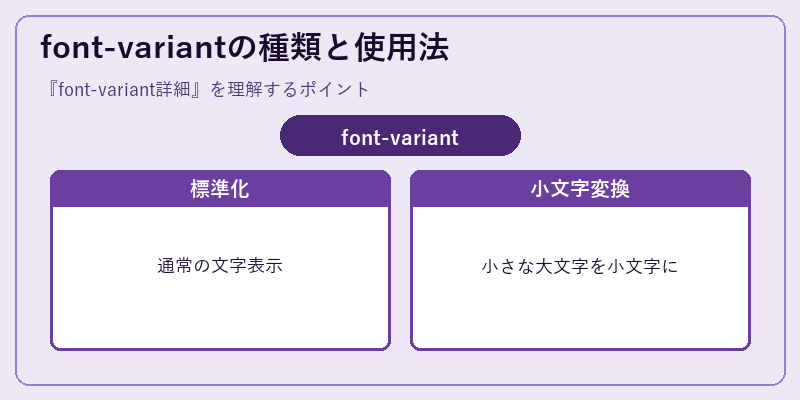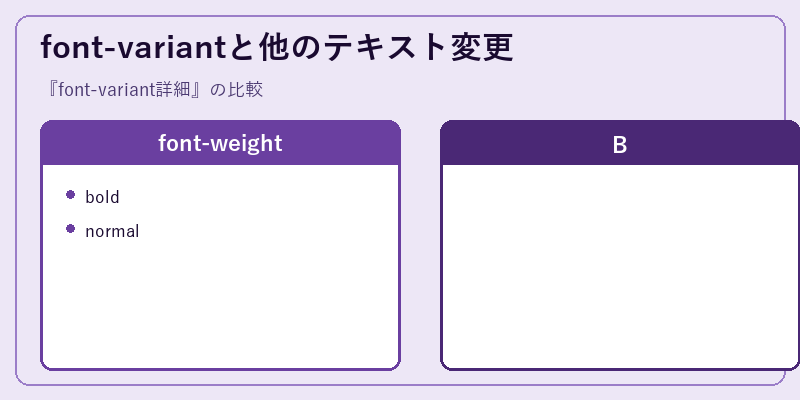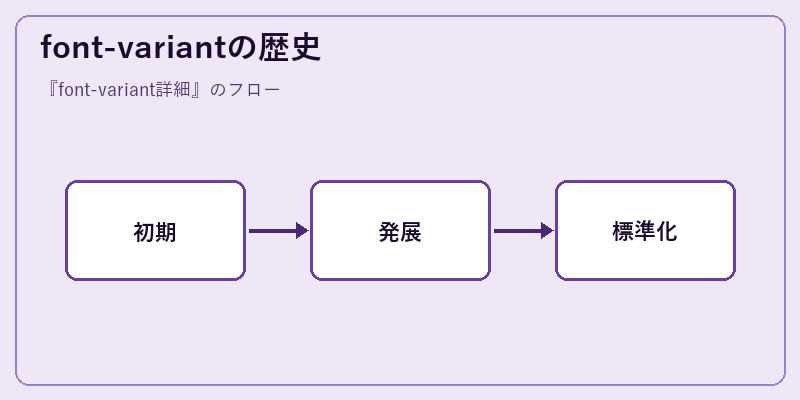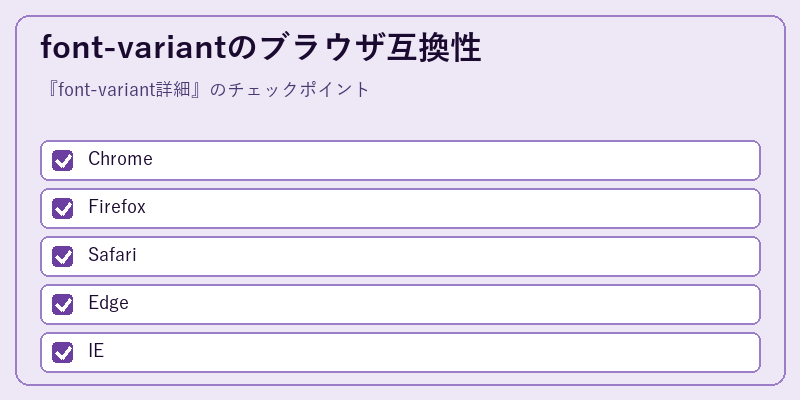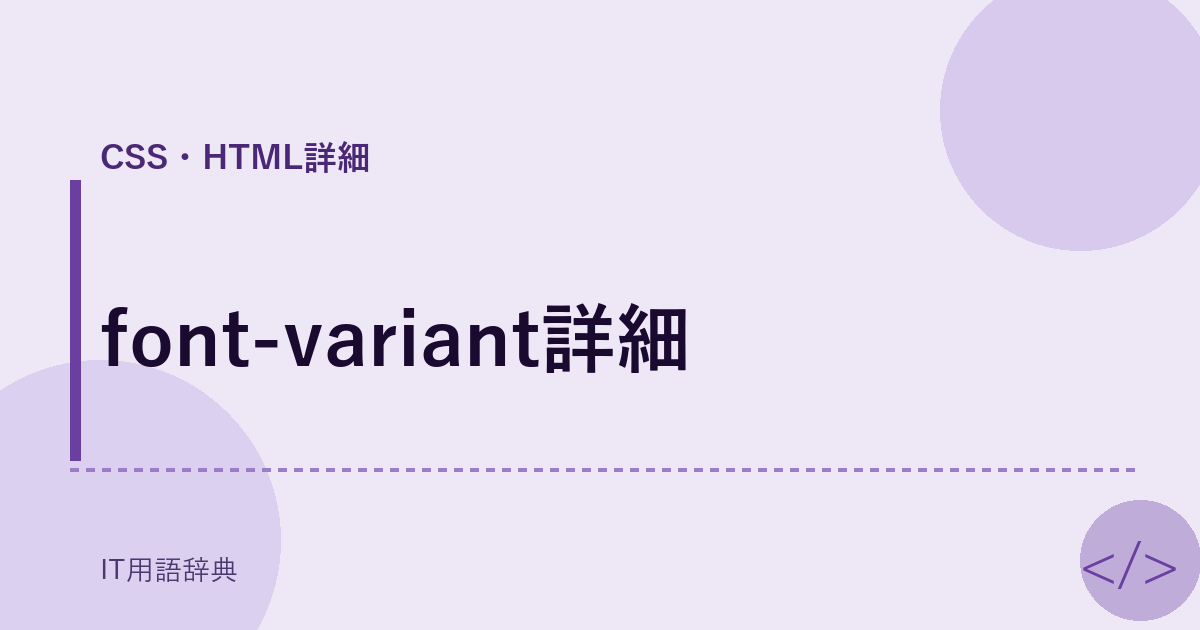
CSS font-variant: テキスト表示を微調整する
font-variant詳細
font-variantはCSSにおいて、文字表現をより詳細にコントロールできるパラメータです。古くから存在しながらも近年のWebデザインではますます重視されるようになりました。
font-variantの種類と使用法
CSSのfont-variantは、テキストを柔軟に操作します。例えば、small-capsで小文字を大文字風に表現したり
.text-class { font-variant: small-caps; } という記述により、文章が洗練された印象を与えます
font-variantと他のテキスト変更
font-variantは、font-weightと同様に文字の重みを調整しますが、表現の方法が異なります。
.text-class { font-weight: bold; }.text-class { font-variant: small-caps; }では、テキスト表現が大きく変わります
font-variantの歴史
1990年代初頭にCSSは誕生しました。その後、Webデザインは進化し、font-variantがより重要になりました
現在では、font-variantは多くのウェブサイトで利用されており、ユーザビリティと視覚的な魅力を高める役割を果たしています
font-variantのブラウザ互換性
font-variantは、全ての主要なWebブラウザでサポートされています。ただし、一部の機能には制限があります
.text-class { font-variant: small-caps; }は、最新版のChromeやFirefoxでは問題なく動作します
まとめ
font-variantはCSSにおいて重要なテキスト表現技術です。この手法を理解し、適切に利用することで、Webページの視覚的な魅力とユーザビリティを向上させることができます